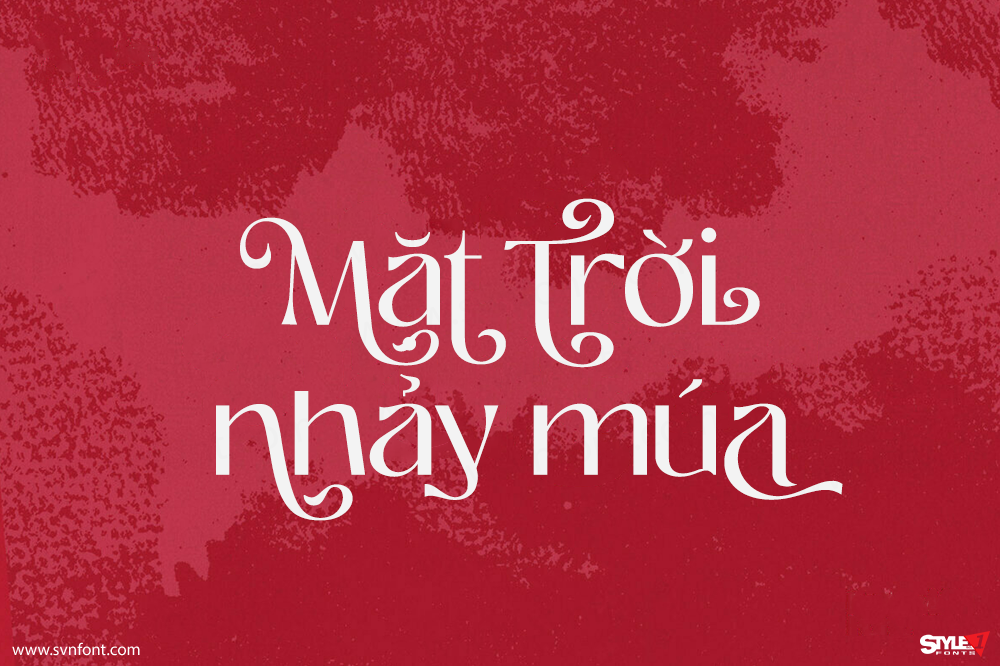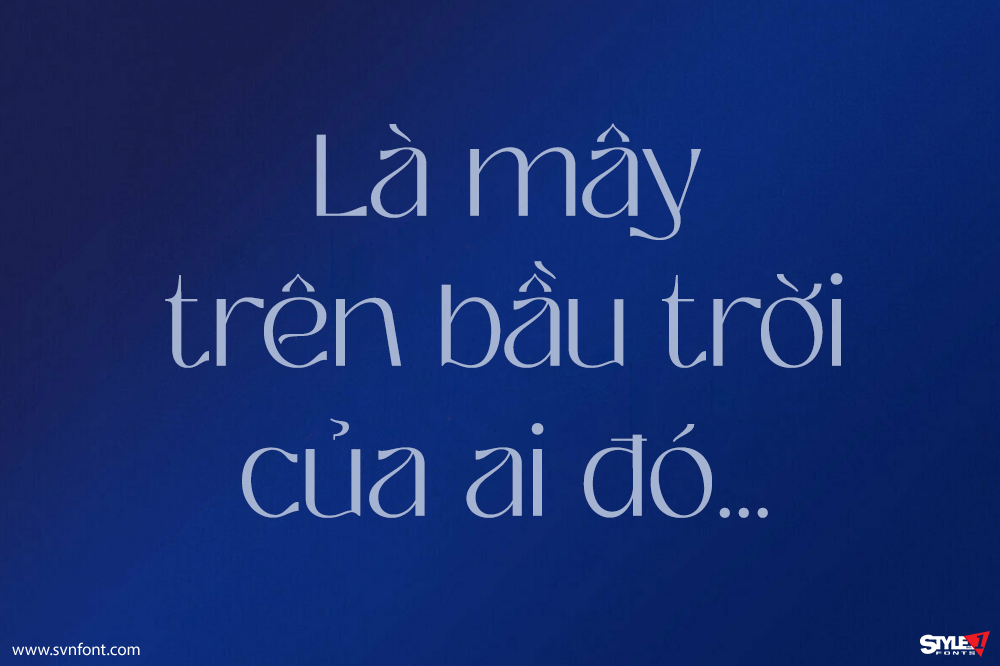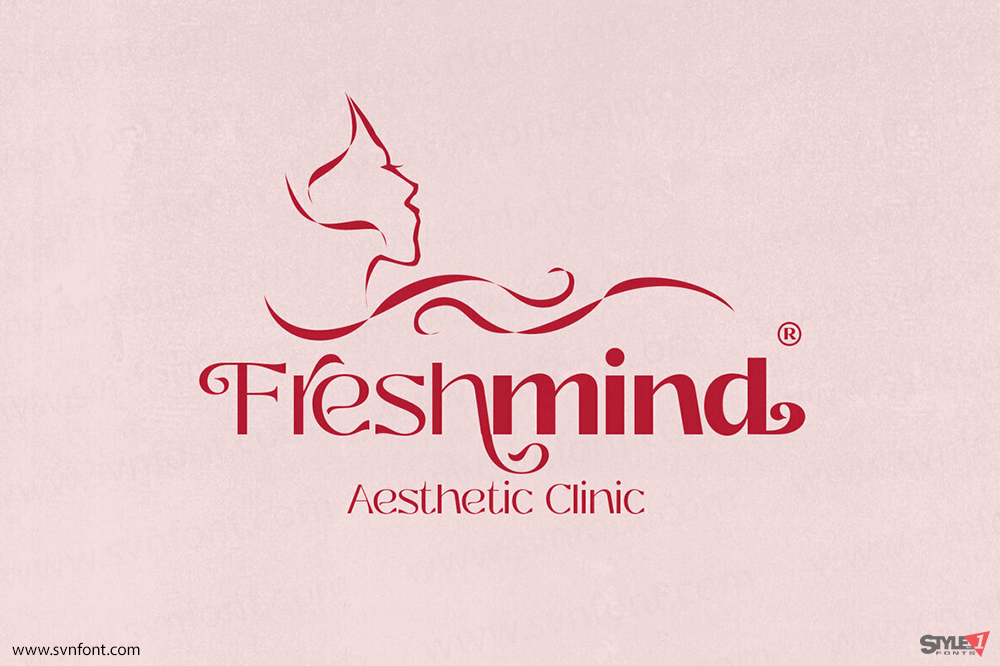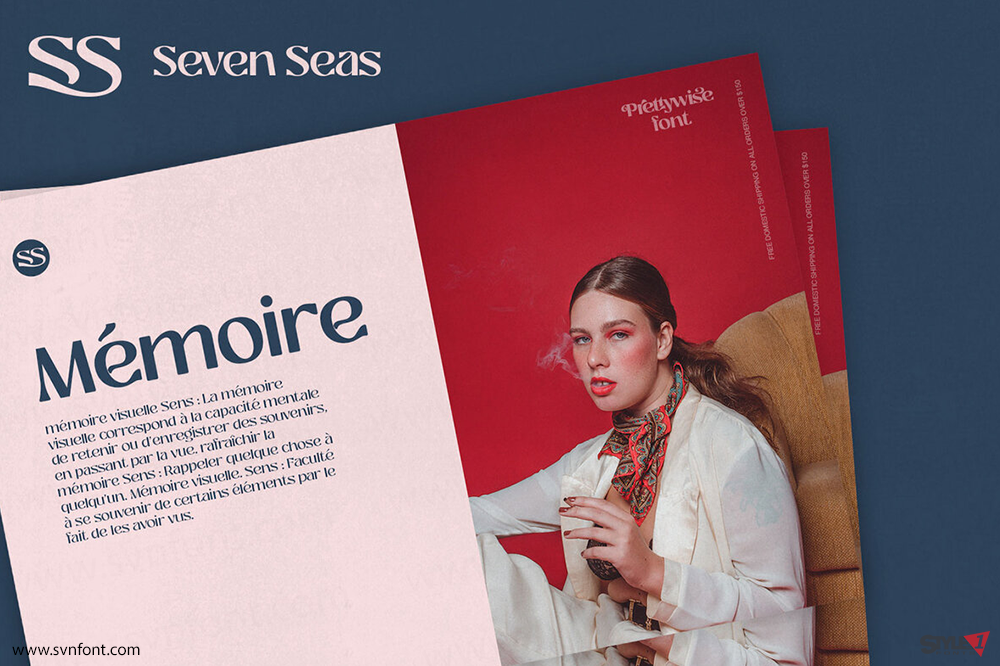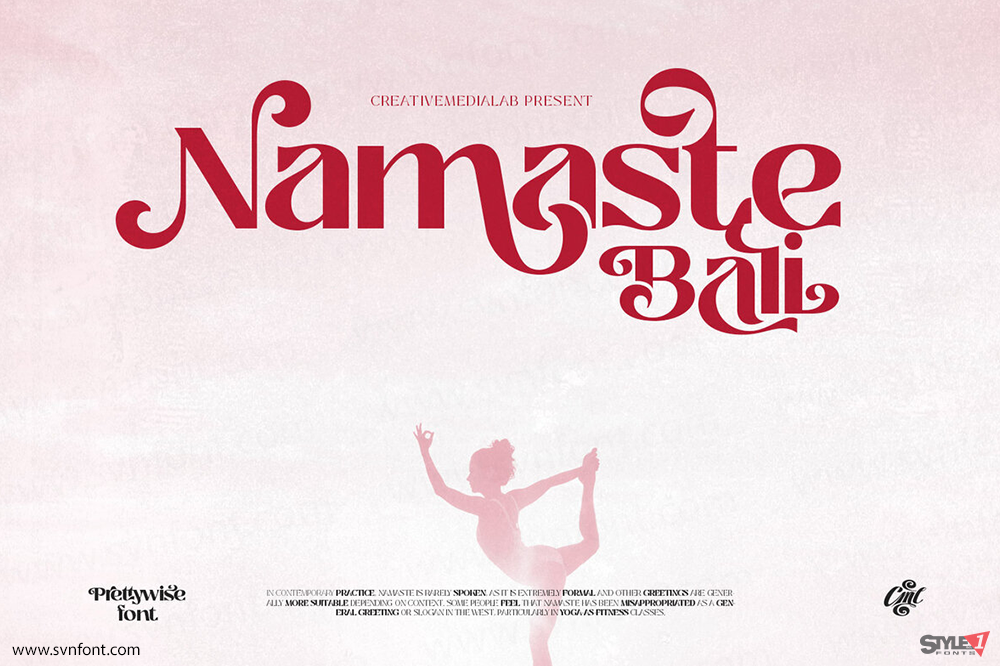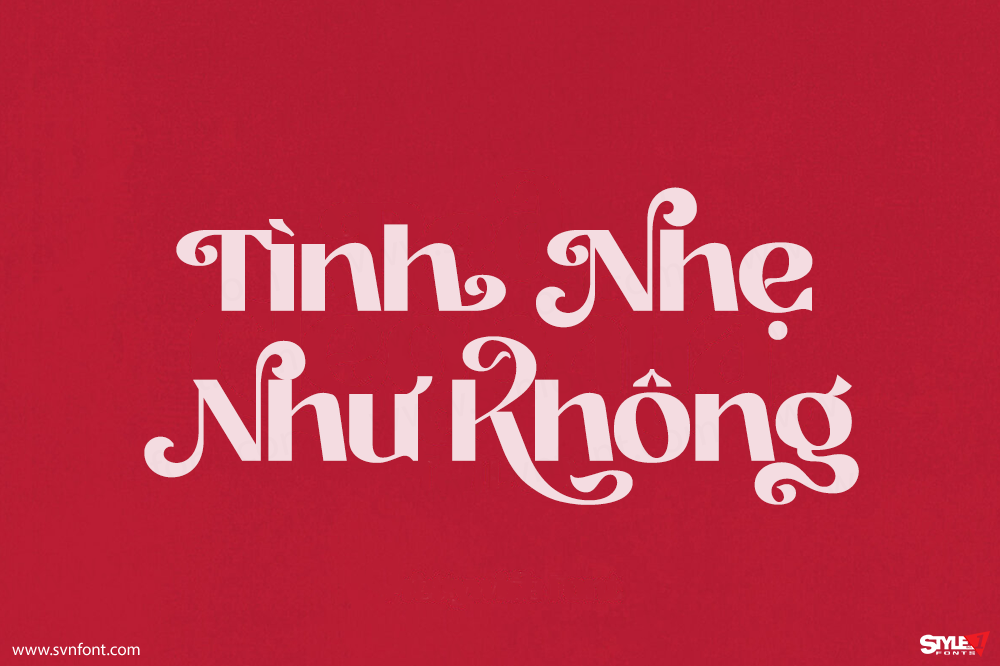
Prettywise – serif typeface hiện đại, độc đáo và đẹp mắt này bao gồm hơn 30 bộ chữ nối (ligatures) và hơn 100 ký tự thay thế (alternates) để bạn thoải mái kết hợp, tạo nên những thiết kế hiển thị hoặc tiêu đề ấn tượng. Họ phông chữ đa năng này có 10 độ đậm, các kiểu biến đổi (variable styles) cũng như hỗ trợ đa ngôn ngữ, số và ký hiệu tiền tệ.
Phù hợp để sử dụng trong nhiều hình thức thiết kế, ví dụ như: tạp chí, logo, thiết kế web, các dự án DIY, trích dẫn, bao bì, bưu thiếp, huy hiệu phong cách cổ điển hoặc retro, âm nhạc cổ điển, kỷ nguyên 60, 70, 80, nhãn dán, nhãn hiệu, chủ đề đám cưới và nhiều hơn nữa. Chúng tôi khuyến nghị sử dụng các chương trình của Adobe.
Nhà thiết kế: Kadek Mahardika
Nhà phát hành: CREATIVE MEDIA LAB